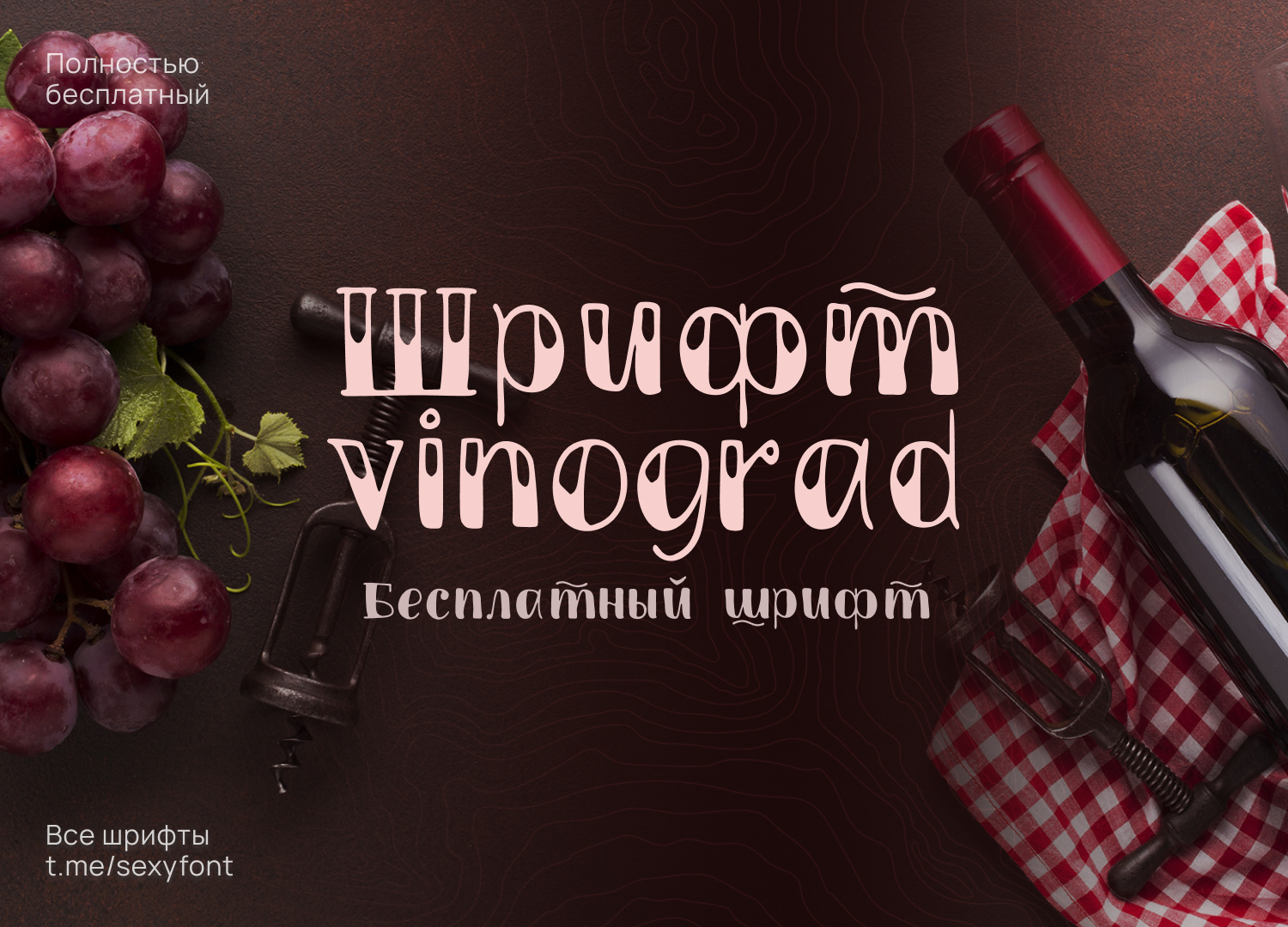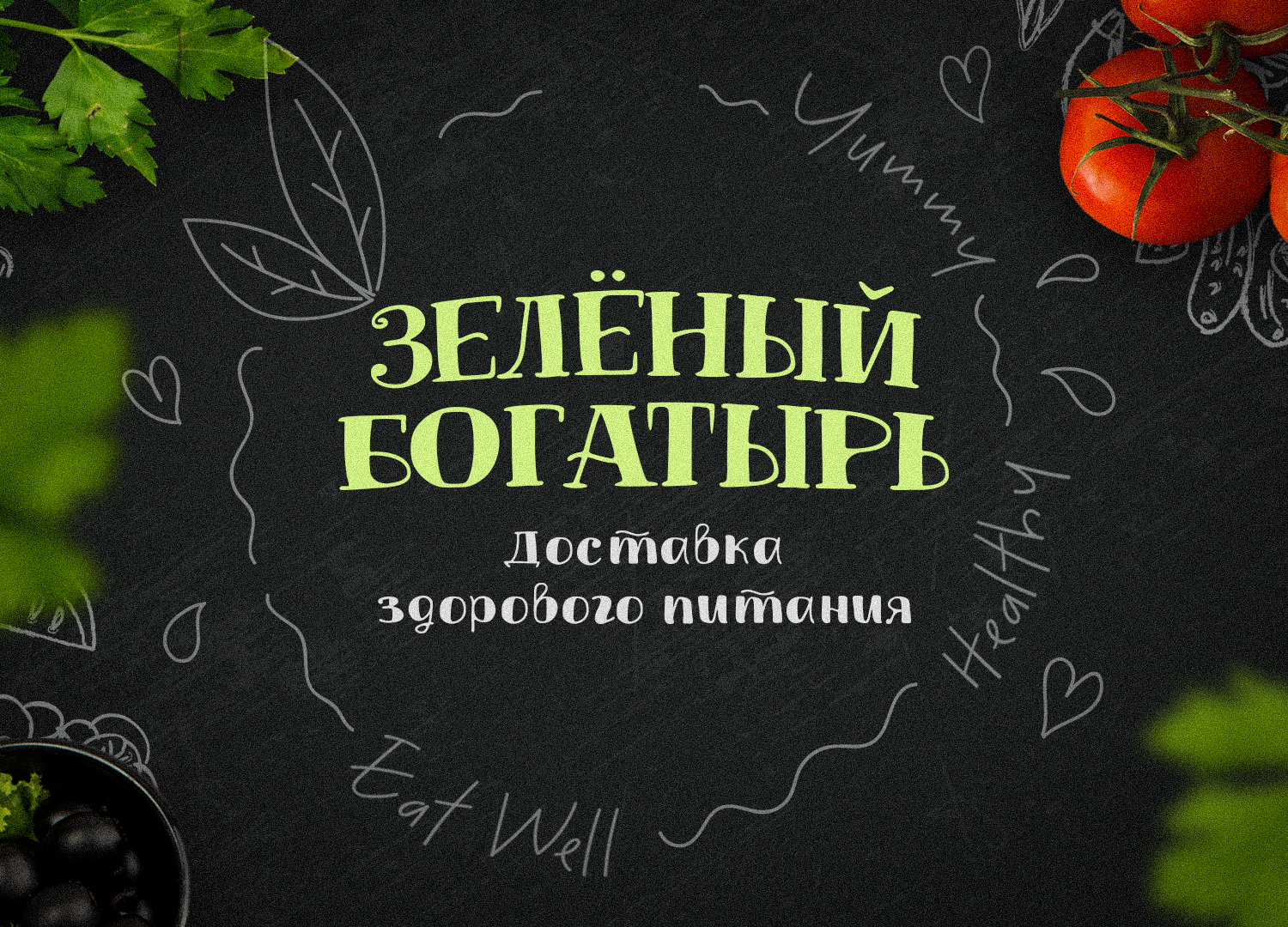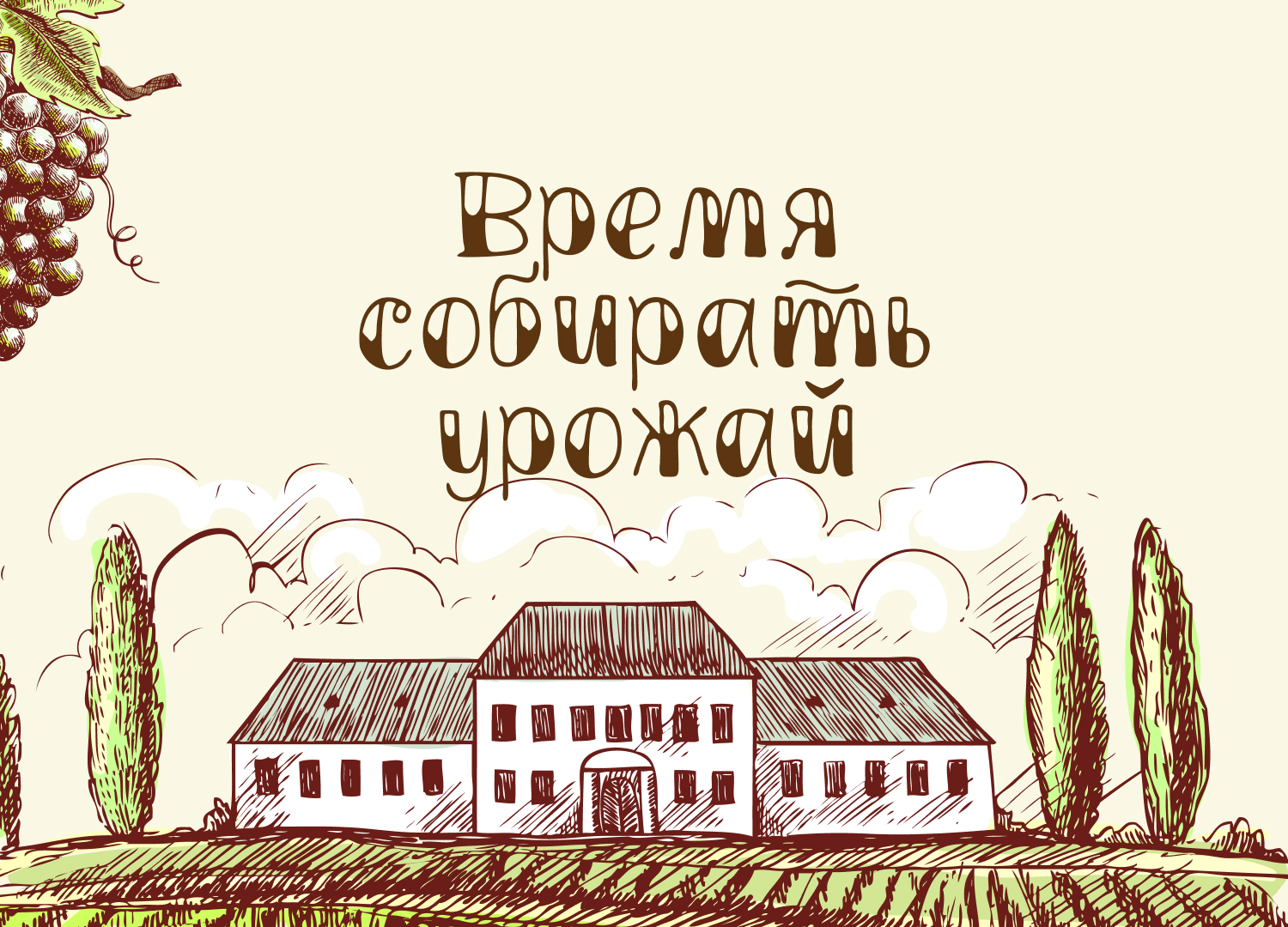
Шрифт Виноград. Кириллица
Мммм…🍇 Виноград. (TM vinograd) Вкусный, сладкий и полностью бесплатный шрифт. Имеется несколько разных начертаний, что делает его более разнообразным. Идеально для тем с едой, детьми, детей из еды еды для детей. Автор: Vova Egoshin